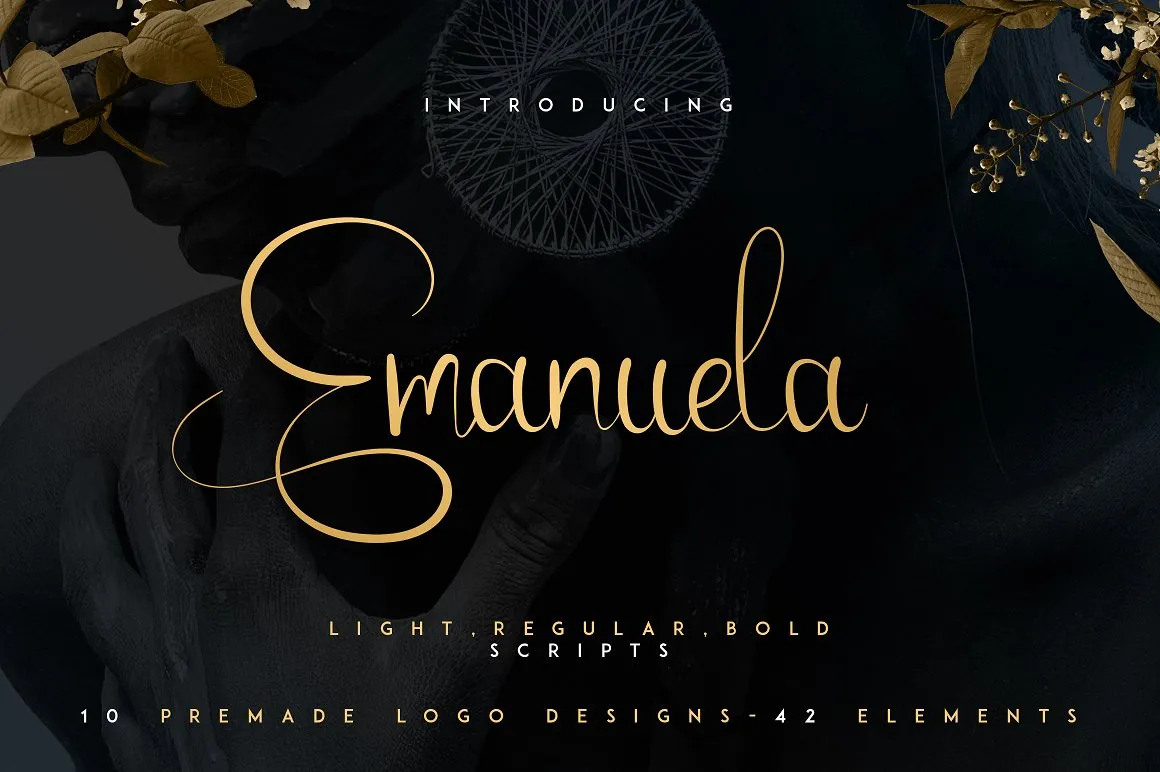
Emanuela Script Font – Download Grátis
A Emanuela Script Font é uma adição encantadora ao seu catálogo de fuentes. Sugerida para designers que valorizam personalidade e estilo autêntico, essa novíssima tipografia é perfeita tanto para projetos de marca quanto para design de interiores ou embalagens de produtos. Com linhas limpas e atraentes, Emanuela oferece uma opção ideal para estilos gráficos mais despojados ou até mesmo como um background complementar em imagens que exibem textos. Ideal tanto para designers de marca quanto para designers de interiores, essa fonte traz um toque único e charmoso à sua criação. Seja em uma etiqueta de produto, a capa de um livro ou até mesmo ao adicionar texto sobre uma imagem de fundo em seu projeto de design, Emanuela Script proporcionará um ar fresco e pessoal que certamente vai destacar qualquer ideia artística. Com a Emanuela Script Font, você está dando vida à sua marca e criatividade com um toque único e autêntico.